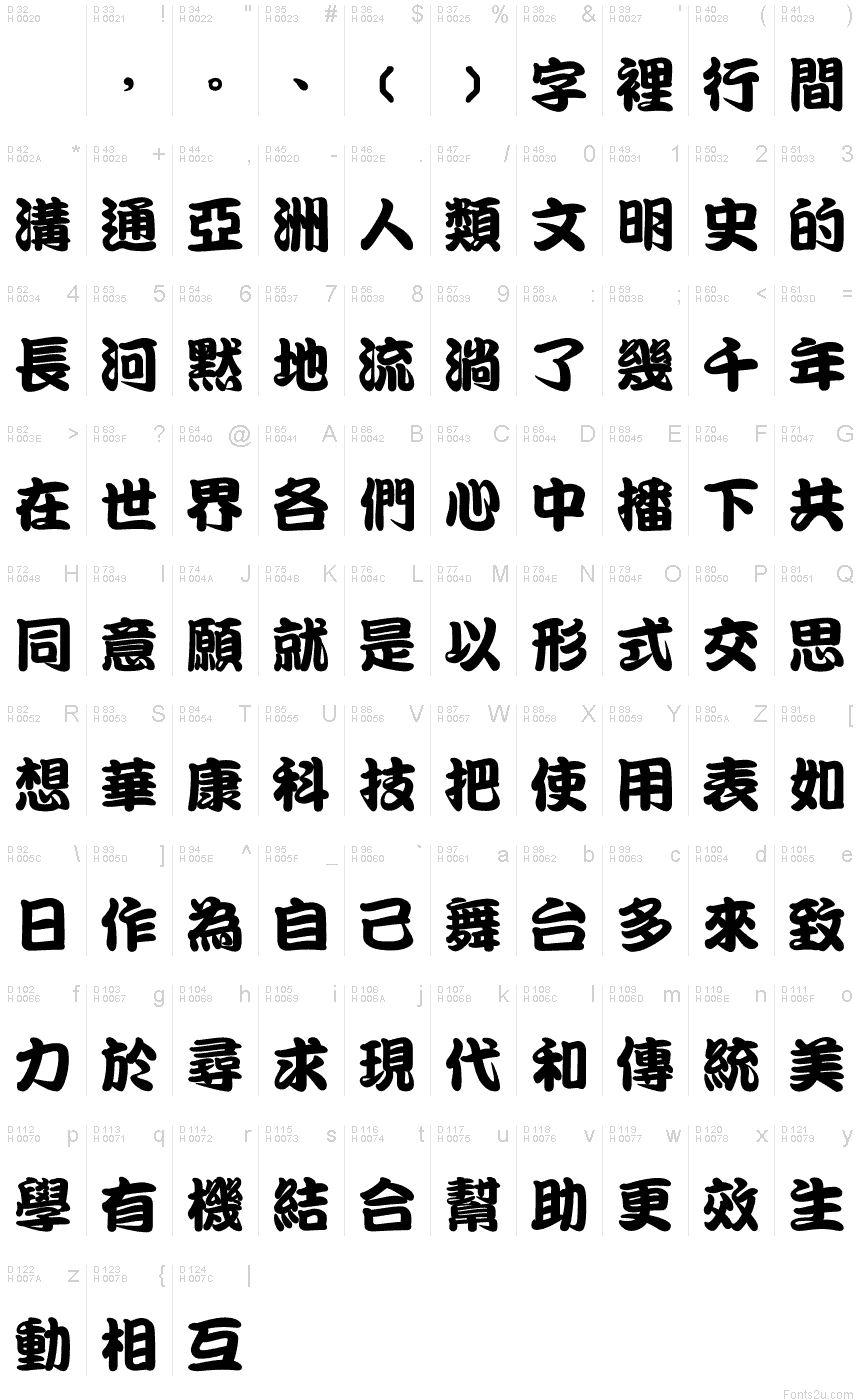
DF Kan Ting Liu 1B von DynaLab Inc. ist eine kostenlose chinesische Pinselschrift mit dem lockeren Schwung von handgemalter Reklame. Sie besticht durch dicke, abgerundete Striche und weiche, fast aufgeblasen wirkende Enden. Die Schrift wirkt lebendig und verspielt statt formell, wobei breite horizontale Schwünge auf kompakte, verknotete Verbindungen treffen, was für eine dichte und rhythmische Textur sorgt.
Diese kostenlose Schrift eignet sich hervorragend für Poster, Gastronomie-Branding, Festival-Grafiken, Titelkarten, Verpackungen und kurze Headlines – überall dort, wo Sie eine warme, nahbare chinesische Handschrift suchen. Auch für knappe Beschriftungen oder Kapitelanfänge ist sie ideal, da die kräftigen, lebendigen Pinselformen viel Ausdrucksstärke bieten, ohne dass man viele Zeichen benötigt.